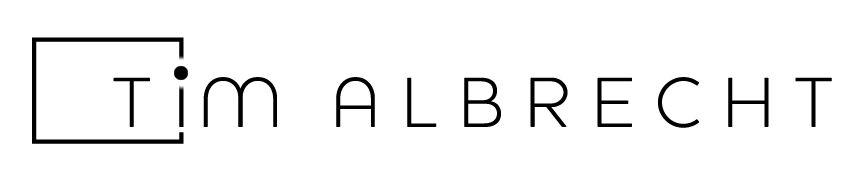
Schriftart für Fotograf/Logo gesucht.
Weil das ja ein Wunschkonzert zu sein scheint: Das kreuzförmige T mag vielleicht die Camera obscura (?) näher erläutern, aber der Lesbarkeit des Namens ist es nicht förderlich. Also ich würde das wieder zurücknehmen.
Und die Strichstärke des Rahmens, demzufolge auch des I, ist der Houschka noch nicht angepasst, sprich: zu stark.
finde beim letzten Entwurf die Lesbarkeit des »T« nicht gegeben, Rahmen wie bereits oben erwähnt etwas zu dick.
Zusätzlich finde ich das »R« unharmonisch: der Bogen ist zu umfangreich und groß und wirkt deshalb von einem zu kleinen Schrägstrich (gibt es da einen typografischen Fachbegriff?) abgestützt. Auch beisst es sich so mit dem davor stehenden »B«, dessen oberer Bogen kleiner und der untere Bogen wohl dem des R« entspricht.
Ist wohl nicht mein Abend ... :neenee: ... ich habe weder Tim noch die Kamera gesehen bevor ihr es klar hingeschrieben habt. Mit dem Rechteck hab ich noch Mühe. Es passt für mich nicht soo ins Logo. Vielleicht liegts am komischen Seitenverhältniss. Es ist weder 3:2 noch 16:9, es ist ungefähr 10:7, also unüblich. Falls allerdings das Kameragehäuse und nicht ein Bild gemeint ist, ist natürlich alles möglich. :?
Grundgedanke war bei dem Rechteck ein Foto und keine Kamera. Das Seitenverhältnis ist 9 x 13, also Fotoformat.
Nur um mal darauf hinzuweisen:
Bei einem Logo muss (wenn es andere grafische Qualitäten hat) nicht zwingend sofort erkennbar sein, von was es abgeleitet wurde.
Ob das jetzt also eine Kamera ist oder ein Bild oder ein Bilderrahmen, ist zwar ein Anlass oder eine Gelegenheit darüber zu reden, aber nicht zwingend eine Schwäche.
Ist ja auch alles noch in der Entwicklungsphase.